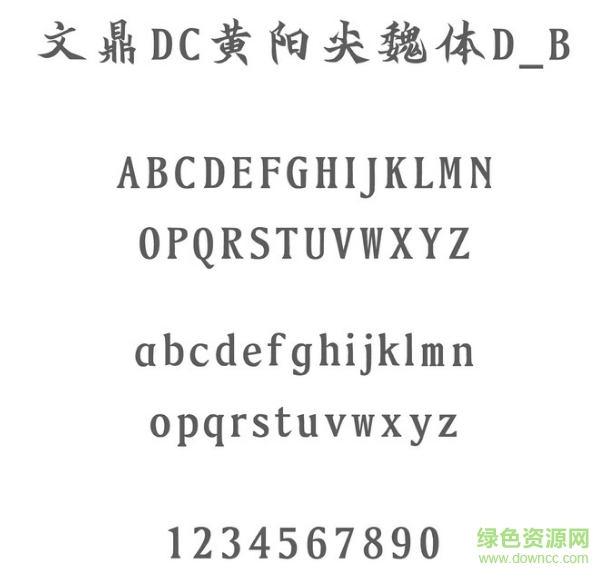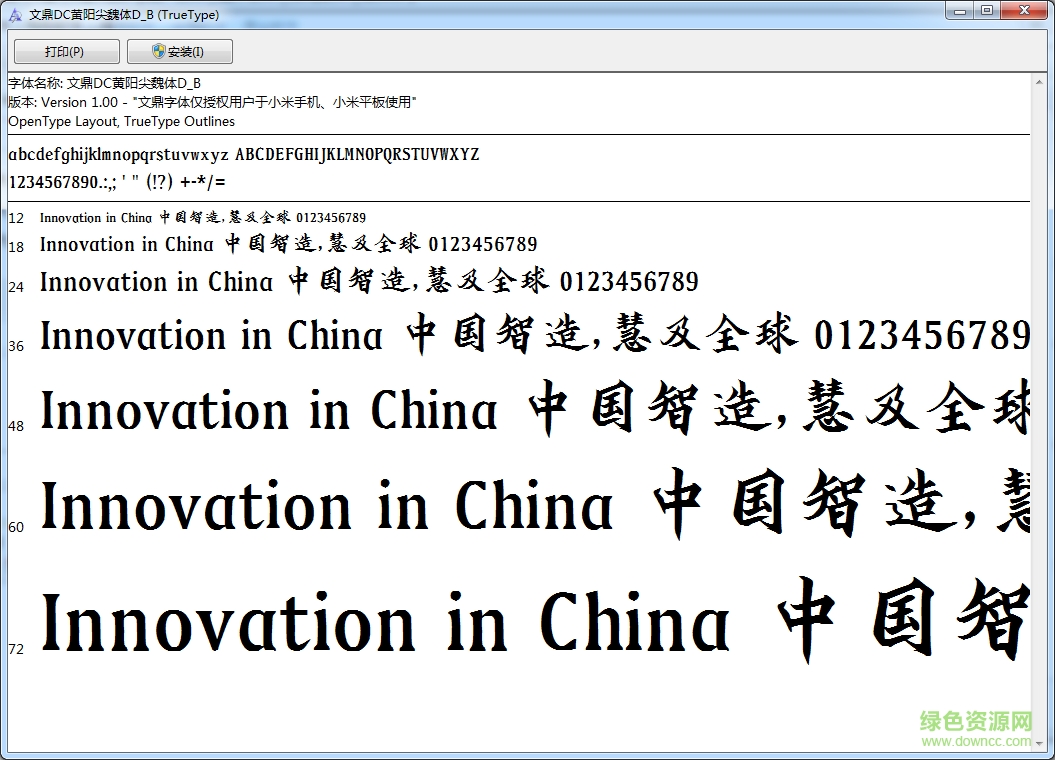
文鼎dc黃陽尖魏體
文鼎dc黃陽尖魏體是一款非常優(yōu)雅的字體,筆鋒纖細(xì),字體非常的工整優(yōu)雅,廣泛用于廣告印刷、包裝設(shè)計(jì)等行業(yè),中英文和阿拉伯?dāng)?shù)字全面支持,歡迎有需要的朋友到綠色資源網(wǎng)下載使用1
文鼎黃陽尖魏體書法字體是知名書法家-黃智陽教授,與文鼎合作開發(fā)的真跡書法字體。教授長時(shí)間逐字用心書寫與設(shè)計(jì),使(尖魏體)突顯了瘦金體的利落美又結(jié)合了魏碑體的方折感,使用上更具有文化意義與時(shí)尚氛圍。
1.文鼎黃陽尖魏體書法字體在形體上彰顯了獨(dú)特的風(fēng)格,挺勁犀利,轉(zhuǎn)折剛健雄強(qiáng),具有現(xiàn)代時(shí)尚感,融合了魏碑體、瘦金體、行書以及裝飾體等多元要素,是一款融合藝術(shù)性、創(chuàng)新性與經(jīng)典性的書法字體。